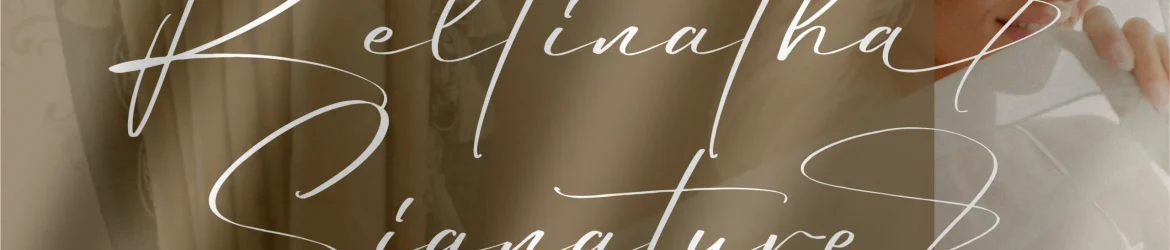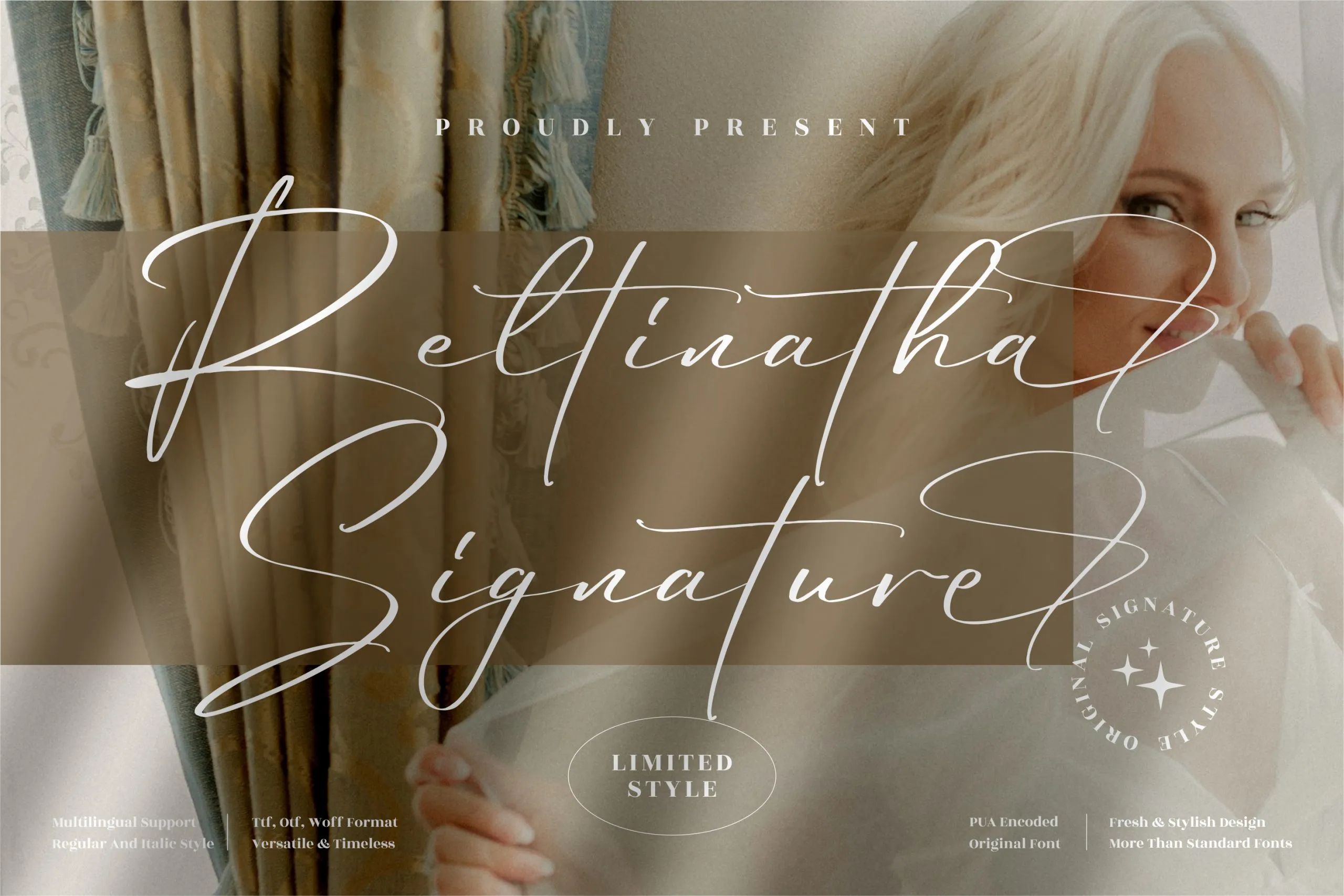
Reltinatha Signature Font – Fonte Grátis
Reltinatha Signature Font
A Reltinatha Signature Font é uma elegante escolha para aqueles que buscam personalidade sofisticada em seus projetos digitais. Criada pela Perspectype Studio, essa premium signature font destaca-se com sua estética minimalista e arredondada, perfeita tanto para criar rótulos de embalagens atraentes quanto para projetos de marca ou design de produtos. Seja você um designer gráfico atento aos detalhes, ou simplesmente alguém que busca uma maneira criativa de enriquecer seus trabalhos com uma assinatura única e personalizada, essa fonte é perfeita. Suas linhas delicadas e sua disposição harmônica fazem dela uma opção ideal para criar um design sofisticado em vários tipos de projetos. Seja para adicionar um toque a seu logo de marca, personalizar uma etiqueta, ou criar um material exclusivo como uma camiseta personalizada, Reltinatha é uma fonte que adiciona valor e estilo a qualquer projeto. Com sua versatilidade e qualidade premium, essa fonte se torna um recurso valioso para qualquer designer que deseja incorporar detalhes finos à suas criações.